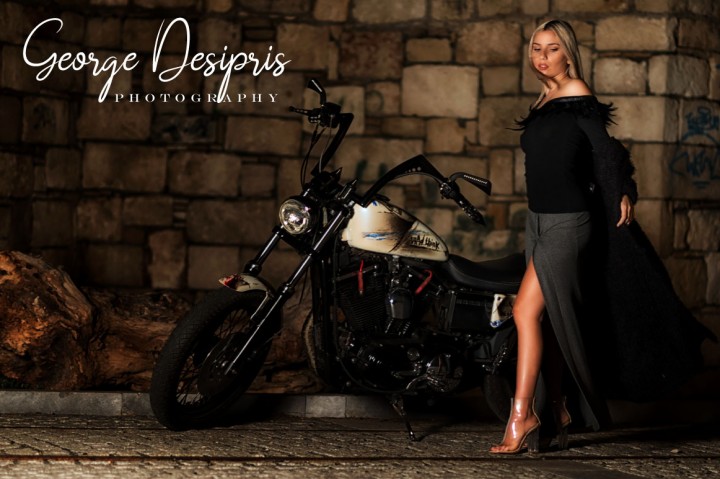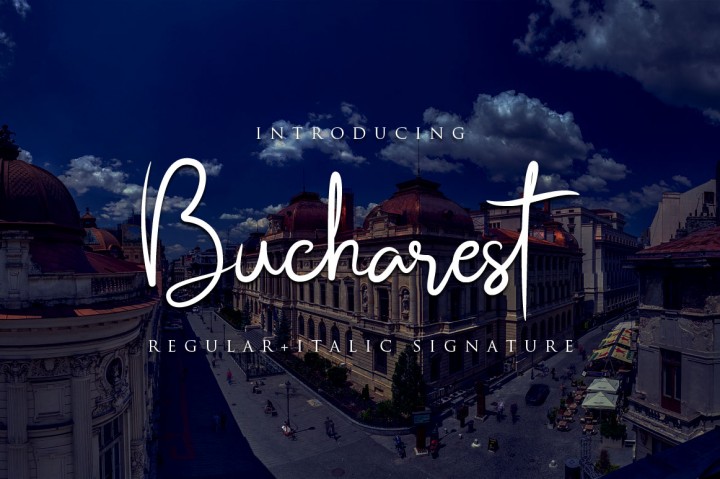
Bucharest Handwriting
Bucharest Handwriting Font
Bucharest adalah font tanda tangan modern dan elegan. Bucharest Anda dapat menerapkan proyek desain apa pun, seperti kartu nama, kartu ucapan, kartu undangan, dan banyak lagi.